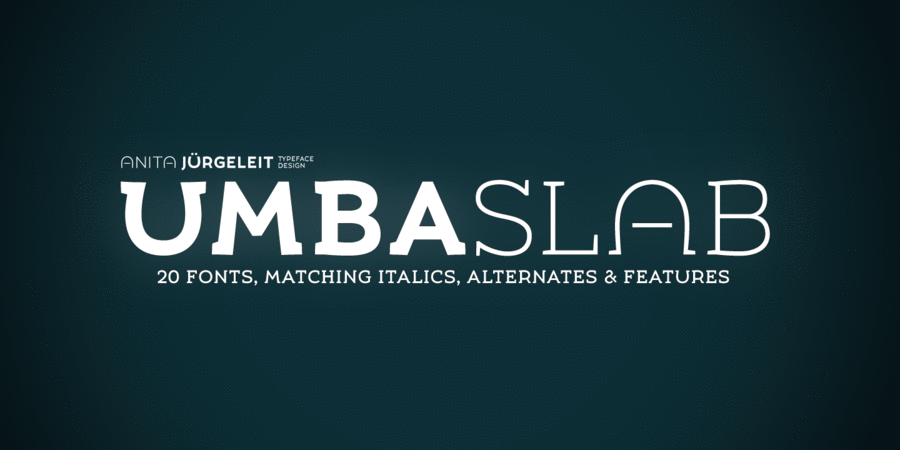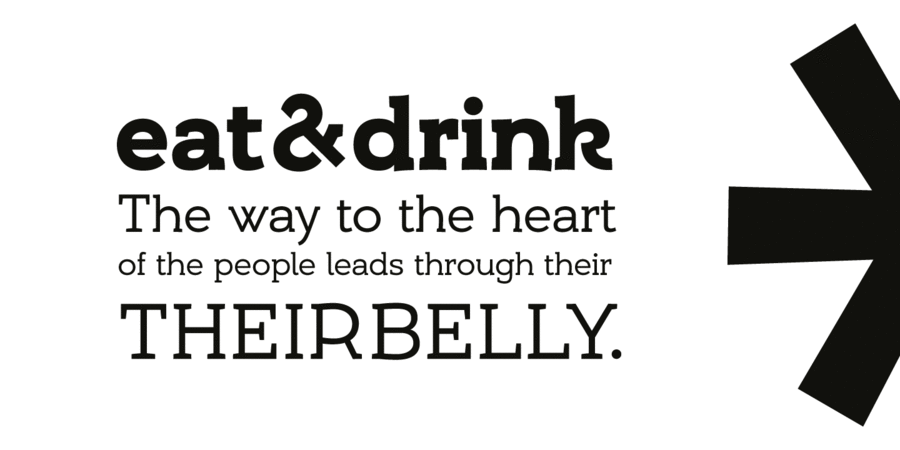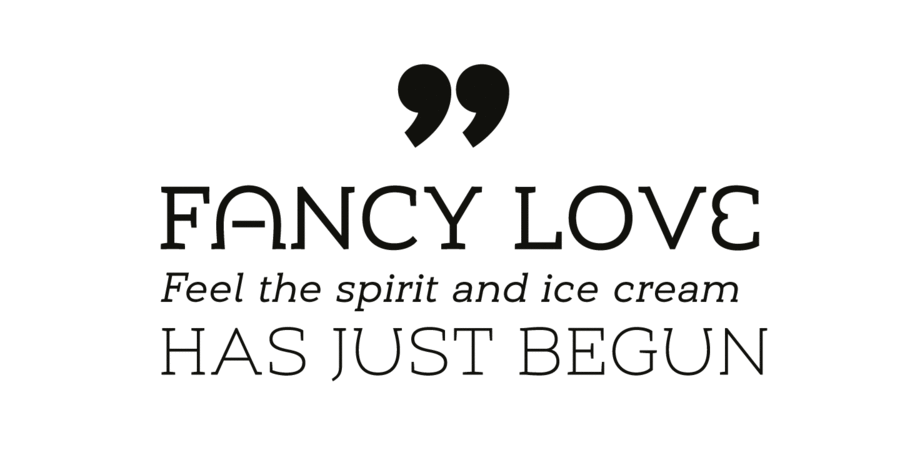
UMBA Slab (30 шрифтів)
UMBA Slab – це досить просте шрифтове сімейство, але воно точно вам запам'ятається. Воно надає унікальності корпоративній ідентифікації та заголовкам завдяки динаміці що наростає від тонкого до жирного накреслення. Ґарнітура містить багато варіацій форми знаків для створення впізнаваної айдентики та цікавої акциденції.
Десять накреслень з насиченостями від Тонкого до Жирного з відповідними курсивами дозволять вирішити будь-яку дизайнерську задачу. Також в сімейство входять 10 накреслень з нестандартними характерними формами літер і ще 10 Caps накреслень.
Шрифт UMBA Slab розробила Аніта Юргелайт в 2019 році.
Асоціації з сімейством шрифтів UMBA SlabОсобистість і характер гарнітури:
делікатний, чистий, легкий, прохолодний, тонкий, сучасний, рівний, якісний, модний, гнучкий, самобутній, оригінальний, міський, неоновий, дротяний, худий, свіжий, культурний, цікавий, характерний, різкий, впевнений, іронічний, артистичний, виразний, яскравий, активний, грайливий, радісний, освічений, стійкий, твердий, розумний, неформальний, помітний, потішний, міцний, здоровий, бадьорий, сильний, доброзичливий, добродушний, добрий, дотепний, незграбний, круглий, щедрий, дерев'яний, студентськиий, творчий, вуличний, ремісничий, важкий, літній, щасливий, гулящий, дозвільний, прикольний, симпатичний, залізний, дивний, химерний, екзотичний, тусовочний, веселий, театральний, святковий
Місто, мода, дієта, дизайн, АСМР, гігієна, бар, кафе, парфумерія, перукарня, інтер'єр, одяг, взуття, гра, дитяча книжка, карти, пригоди, канцтовари, фломастери, годинник, графіка, ілюстрація, анімація, мультфільм, магазин, їжа, сніданок, олівці, іграшка, розваги, дача, хенд мейд, відпочинок, закуска, фаст фуд, торгівля, школа, щоденник, м'ясо, ферма, обід, вечеря, гамбургер, гумор, табір, гурток, розфарбування, спеції, зошит, конструктор, кубики, кузня, вечірка, тусовка, коктейль, атракціон, свято, дискотека, аквадискотека Гарнітура має ознаки стилів: